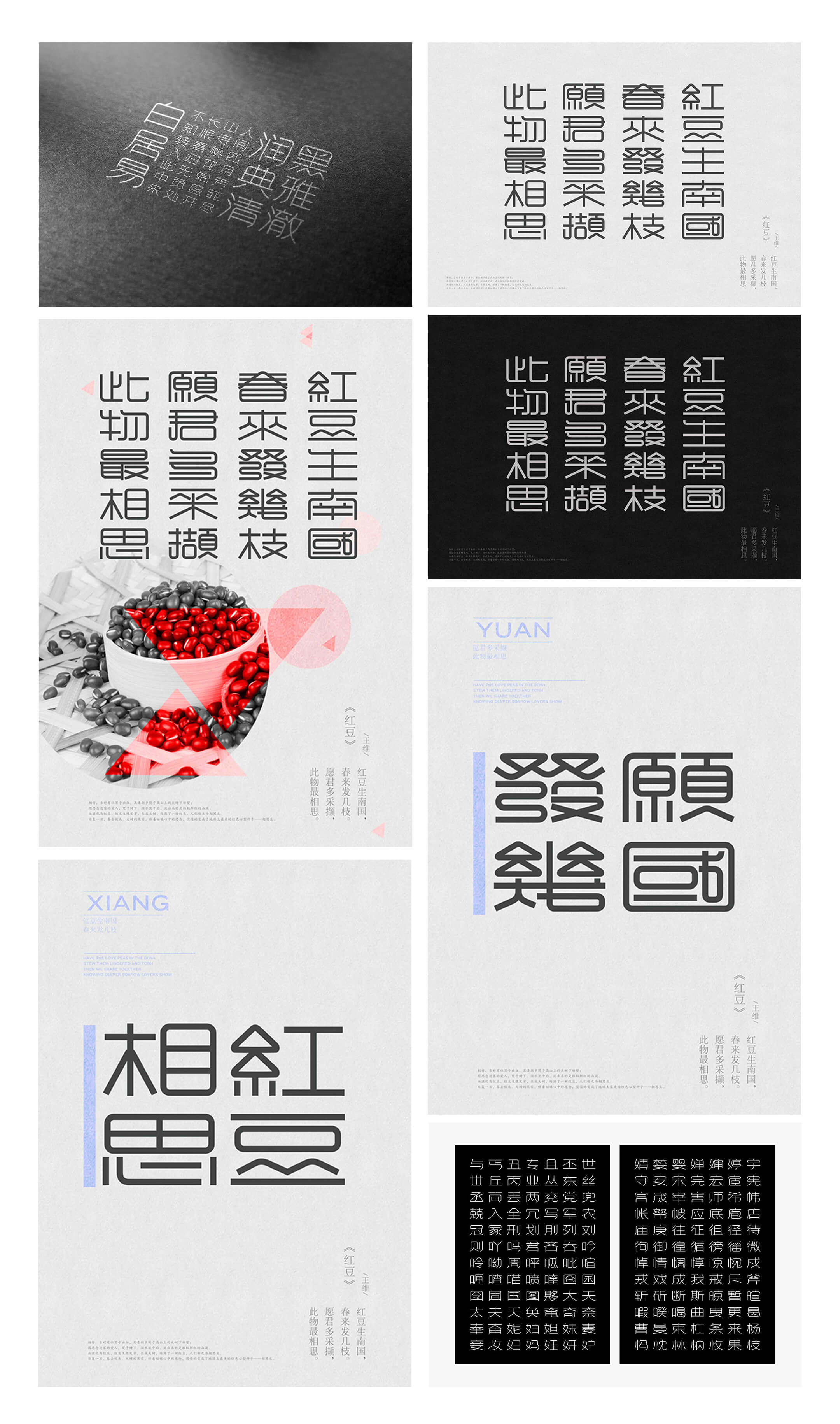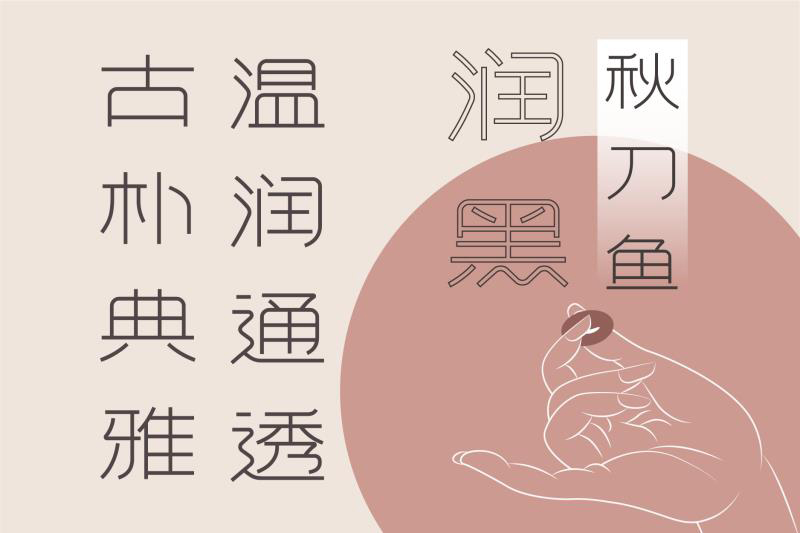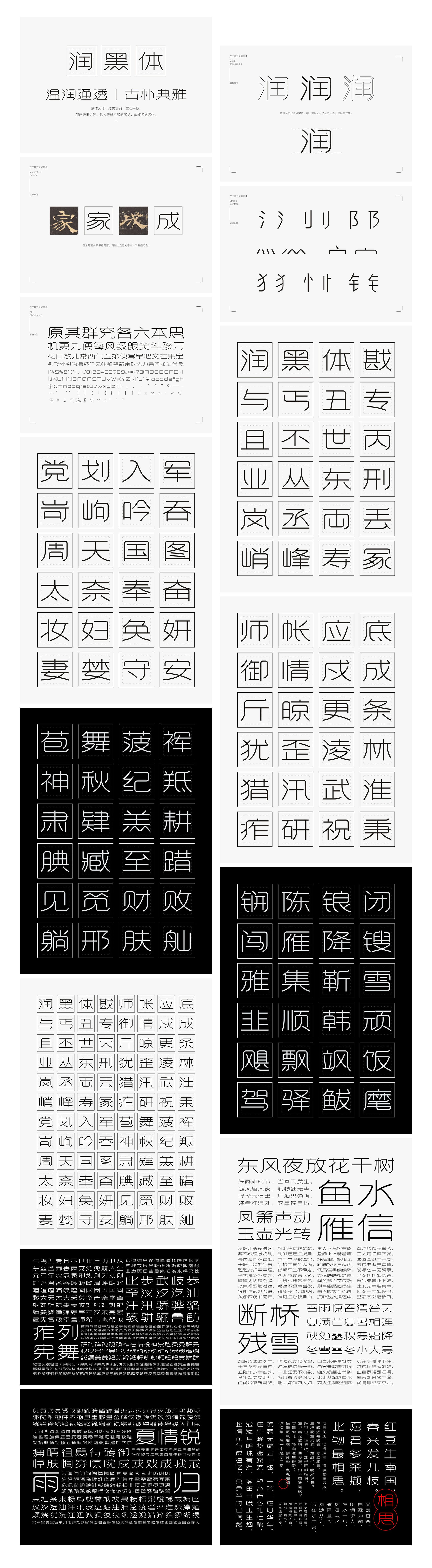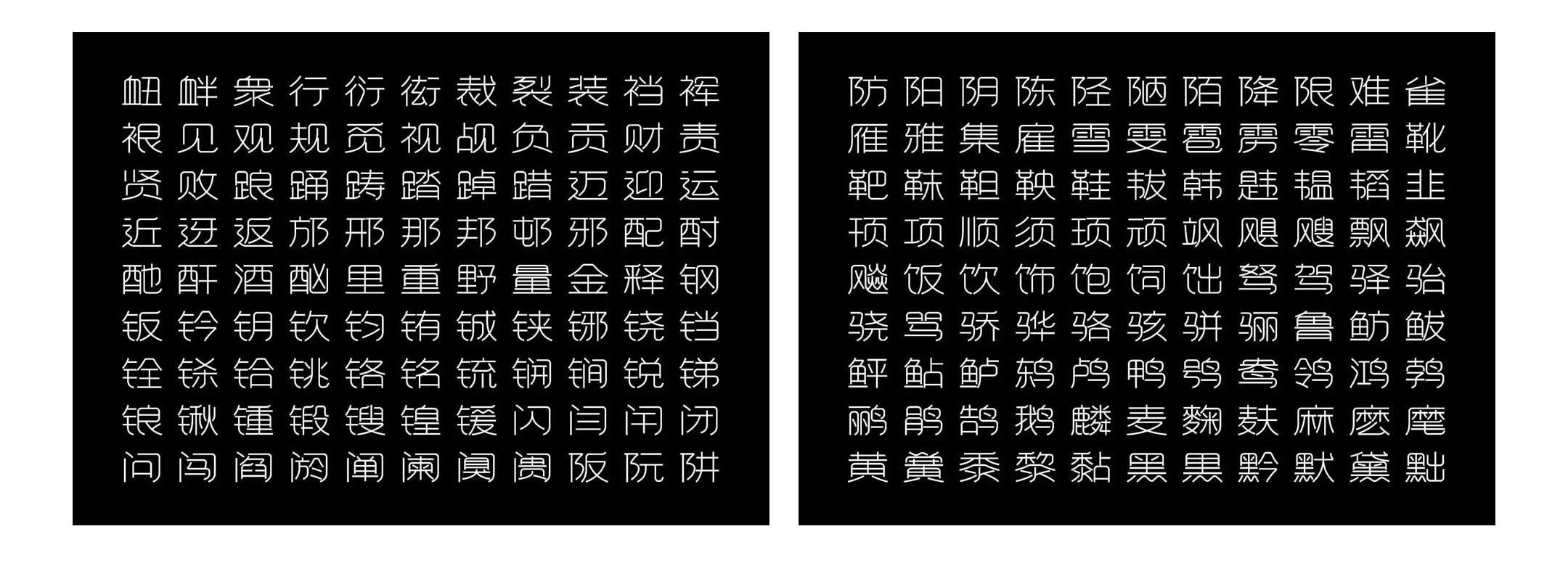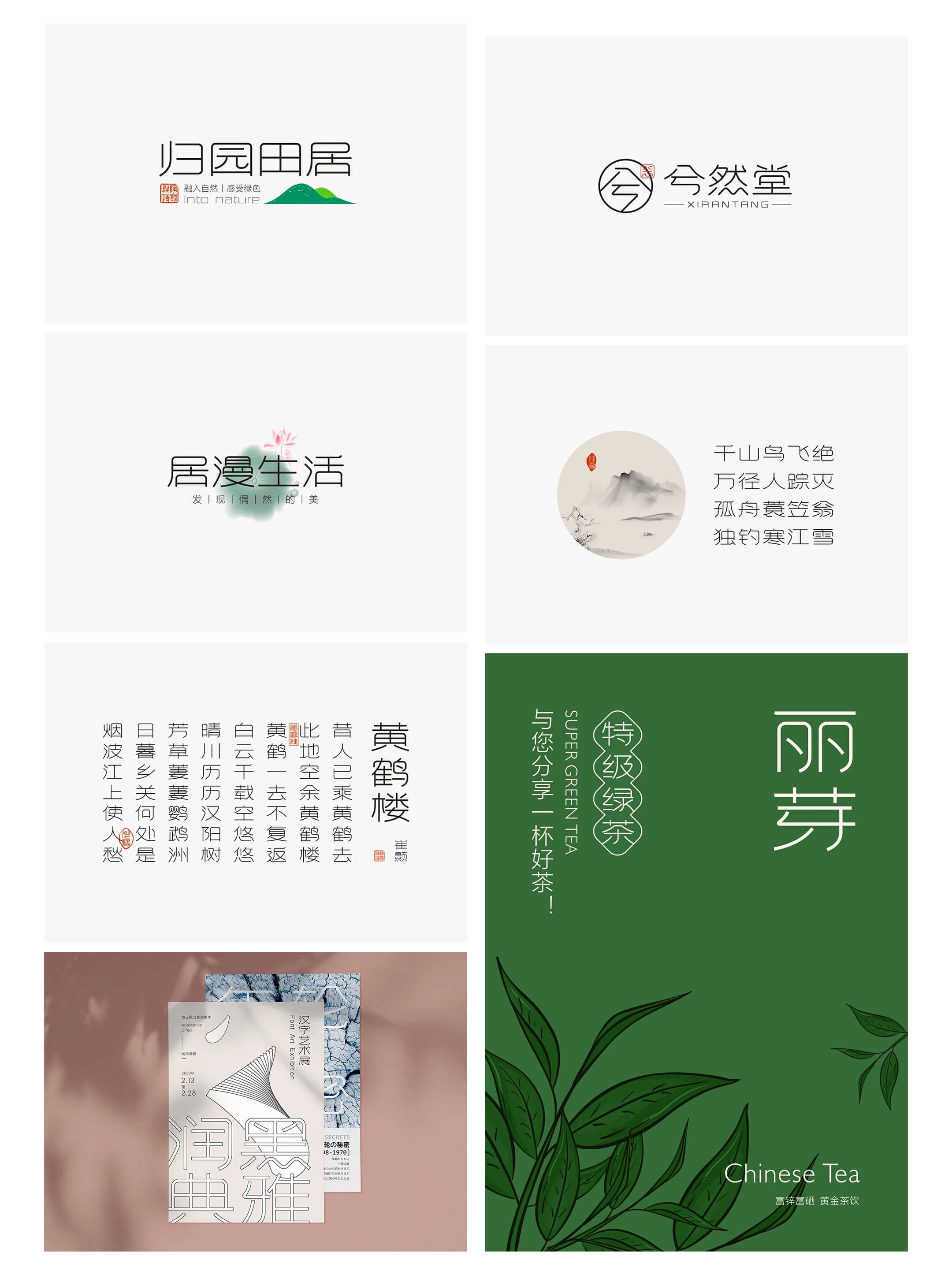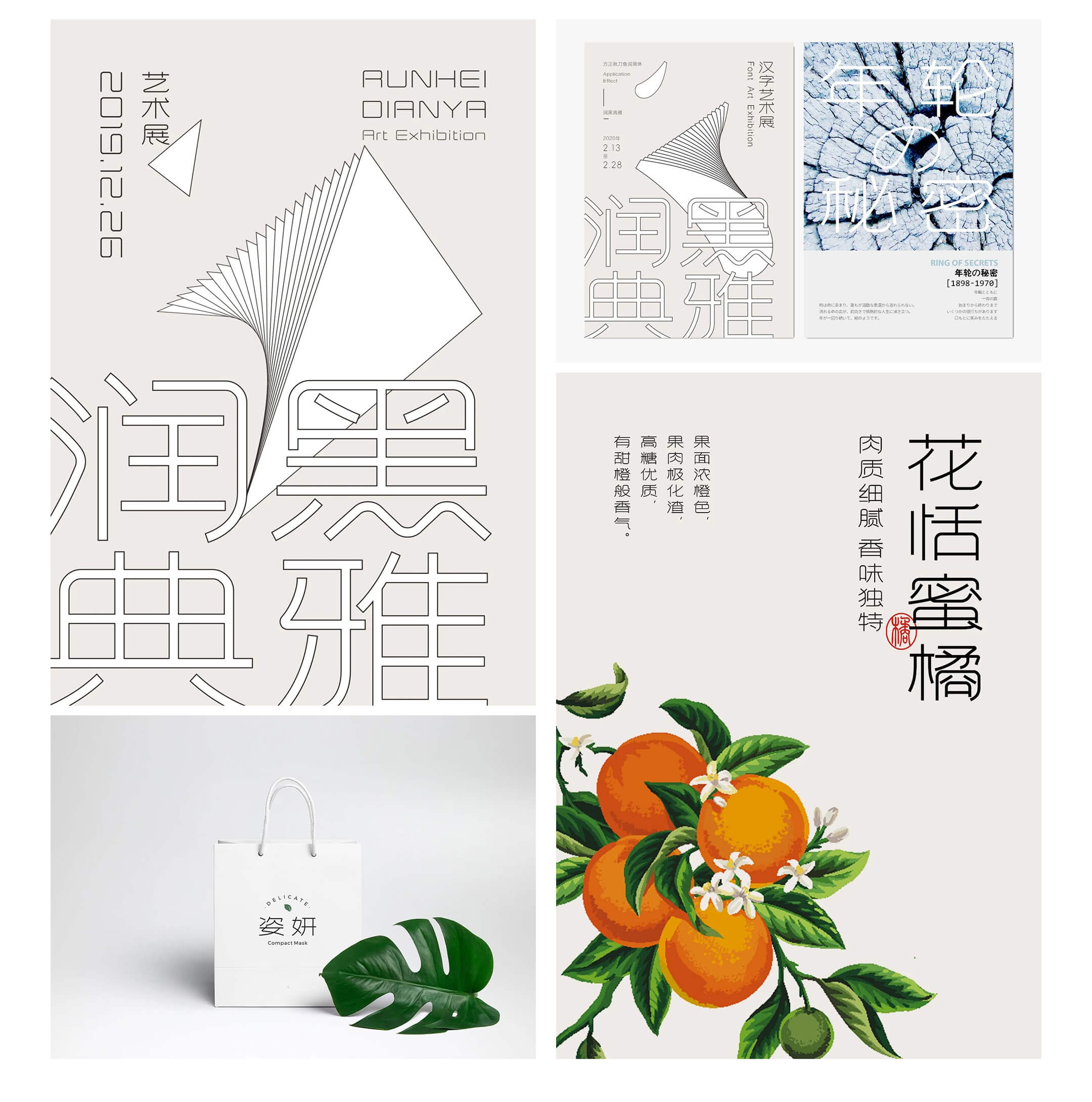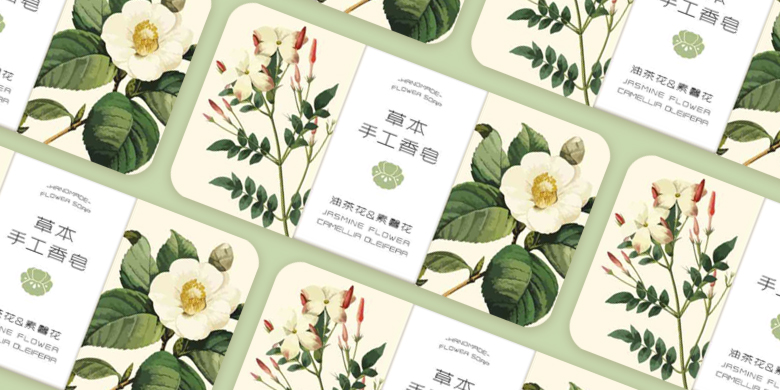
方正秋刀鱼润黑
作者秋刀鱼,本名姜鹏飞,这款字体的灵感来自于一首古诗《相思》,意在表现一种传统委婉的情感,作者早些年做过一篇字体设计帖子,以文字与海报的形式结合,去体现传统之美。后来经过不断尝试与优化,最终确定将它做成一套完整的字库,其字为黑体大形,结构宽扁,重心平稳,笔画纤细温润,给人典雅平和的感觉,故取名润黑体,一些笔画的设计参考隶书的感觉,整体有传统古朴的韵味。
温润如玉、暖人心扉
自古以来,艺术创作都讲究“诗画相通”,诗的意境与画的形象互相映衬、相得益彰,以此寻找情感表达的共性。在现代艺术创作中,也有不少创作者从古代诗词中汲取养分,通过对诗词歌赋意境的斟酌、品味,构建出别具风格的巧思之作。
设计师秋刀鱼(本名姜鹏飞),便从古诗《相思》中寻求灵感,创作出一组字体海报,意与“愿君多采撷,此物最相思”的婉转诗句产生文学上的共鸣,表现委婉而暖心的情感,以字体展现中国古典文化之美。
在不断的尝试与优化之后,最终决定与方正字库签约,将这个字体创意做成一套完整的计算机字库。经过一年多时间的设计与制作,方正秋刀鱼润黑正式发布。让我们来欣赏一下这款气韵典雅的创意字体。
方正秋刀鱼润黑为黑体大形,结构宽扁、重心平稳,笔画纤细温润,给人典雅平和的感觉,部分笔画借鉴了隶书的笔形特征,整体有典雅朴素的韵味。这款字体笔画纤柔传统,让人感觉轻松舒适,适用于标题排版、海报设计、产品包装、品牌LOGO名称等。
温润资天质,清贞禀自然。
以字体之美,展现传统之新貌。